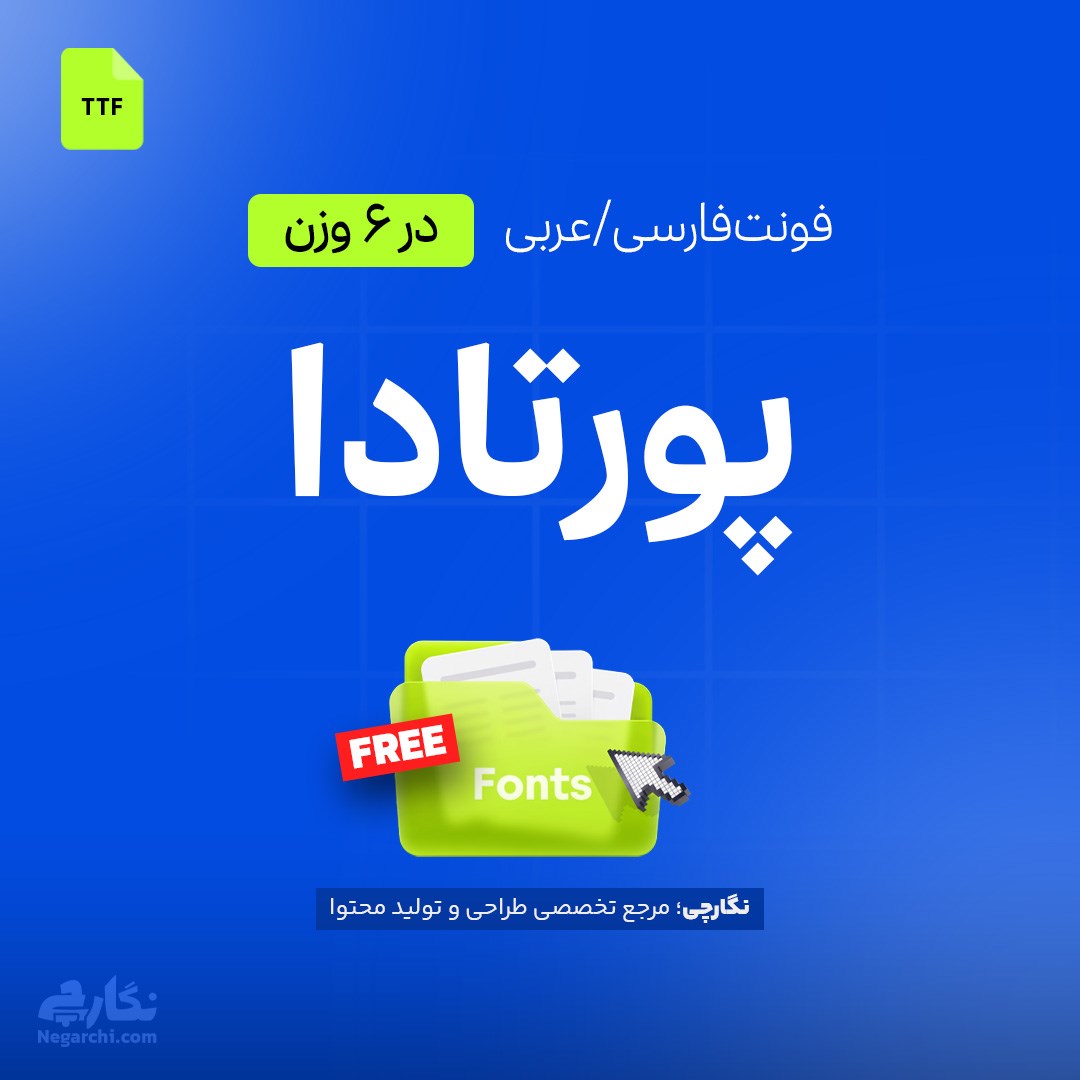
فونت فارسی/عربی پورتادا Portada یک فونت سریف خوانا و حرفهای با پشتیبانی از حروف فارسی، طراحی چندزبانه و ۱۳ فایل و وزن است که برای تایپ متن، تیتر، صفحهآرایی، رابط کاربری و انیمیشن کاربرد دارد.
فونت فارسی پورتادا یک فونت سریف جذاب و خوانا است که در اصل برای زبان عربی طراحی شده، اما برای نوشتن کلمات فارسی نیز مناسب است و در استفاده از حروف گ، چ، پ و ژ با مشکلی مواجه نخواهید شد. ساختار این فونت، آن را برای پروژههای رسمی و غیررسمی مناسب میکند.
فونت پرتادا فونتی سریف با خوانایی بالا و ساختاری متفاوت است که در پروژههای مختلف طراحی گرافیک قابل استفاده است. این فونت دارای ۱۳ فایل و 6 وزن بوده و علاوه بر زبان عربی، از حروف فارسی نیز پشتیبانی میکند. چندزبانه بودن فونت پورتادا باعث میشود بتوان از آن در پروژههایی با محتوای متنوع زبانی استفاده کرد.
فونت پورتادا با توجه به ظاهر سریف و خوانایی مناسب، برای استفاده در موارد مختلف کاربرد دارد، از جمله:
فونت عربی پورتادا با وجود اینکه در اصل یک فونت عربی است، امکان تایپ حروف فارسی را نیز فراهم میکند. بنابراین میتوان از آن برای محتوای فارسی و عربی در پروژههای مختلف استفاده کرد. وجود حروف فارسی و ساختار چندزبانه، پورتادا را به گزینهای کاربردی برای طراحانی تبدیل کرده است که به دنبال یک فونت سریف متفاوت برای پروژههای خود هستند.
بله، فونت پورتادا با وجود اینکه در اصل یک فونت عربی است، برای تایپ فارسی نیز قابل استفاده است و از حروف فارسی پشتیبانی میکند. حروف «گ، چ، پ و ژ» نیز در نوشتن کلمات فارسی قابل استفاده هستند. به همین دلیل میتوان از فونت پورتادا برای طراحی و تایپ متنهای فارسی در پروژههای گرافیکی، صفحهآرایی، رابط کاربری، عنوان و تیتر استفاده کرد و محدودیت رایج برخی فونتهای عربی در حروف فارسی را نداشت.
فونت پورتادا به دلیل ساختار سریف و خوانایی مناسب، در پروژههای مختلف رسمی و غیررسمی قابل استفاده است. از این فونت میتوان برای طراحی عنوان و تیتر، سربرگ، تابلو و سردر مغازهها و اماکن، صفحهآرایی، تایپ متن، طراحی رابط کاربری و ساخت انیمیشن استفاده کرد. ظاهر متفاوت پورتادا باعث میشود علاوه بر متنهای معمول، در بخشهای گرافیکی که نوع نمایش حروف اهمیت دارد نیز کاربرد داشته باشد.
فونت پرتادا در مجموع دارای ۱۳ فایل و 6 وزن است و این تنوع به طراح اجازه میدهد بسته به نوع پروژه و میزان ضخامت مورد نیاز، گزینه مناسبتری را انتخاب کند. وجود وزنهای مختلف برای طراحی تیتر، متن، رابط کاربری و سایر بخشهای گرافیکی اهمیت دارد، زیرا میتوان از ضخامتهای متفاوت برای ایجاد سلسلهمراتب بصری در یک طرح استفاده کرد و ظاهر نوشتهها را متناسب با کاربرد مورد نظر تنظیم کرد.
بله، فونت پورتادا یک فونت چندزبانه است و علاوه بر کاربرد در زبان عربی، امکان استفاده از حروف فارسی را نیز فراهم میکند. این ویژگی باعث میشود پورتادا برای پروژههایی که محتوای فارسی و عربی دارند گزینه مناسبی باشد. وجود حروف فارسی از جمله «گ، چ، پ و ژ» نیز امکان تایپ کلمات فارسی را بدون مشکل فراهم میکند و استفاده از آن را در پروژههای گرافیکی و متنی متنوعتر میسازد.